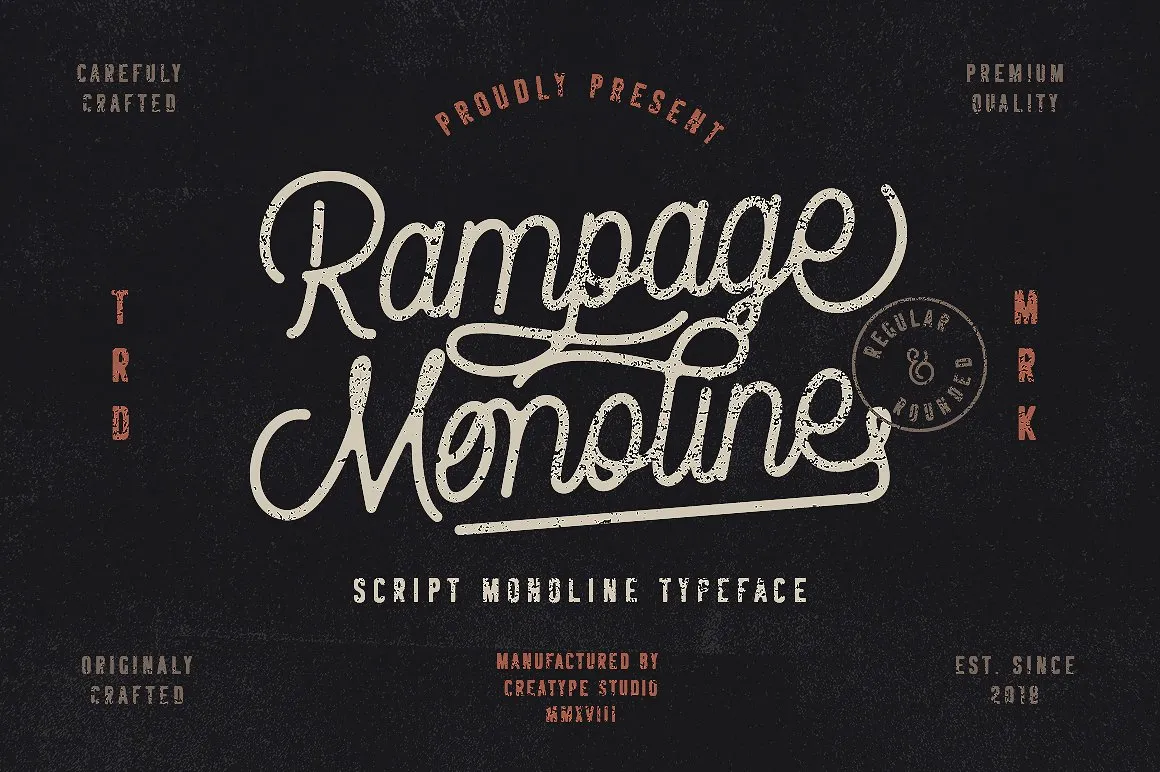
Rampage Monoline Script Font – Download Grátis
Descubra uma nova fonte tipo Rampage Monoline Script Font para seu projeto mais criativo. Esta fonte vintage monoline é uma criação do designer 24Design e traz um estilo elegante e sofisticado que adiciona um toque de movimento e elegância a qualquer projeto visual. Através de sua interface de escrita fluida, o Rampage Monoline surge tanto no formato regular quanto em versão redonda, tornando-se uma escolha perfeita para aplicativos em ambientes expositivos como branding, logotipos, design de casamentos, posts nas redes sociais, anúncios, embalagens de produtos e materiais de convite. Seja você criando arte digital ou trabalhando com fotografias, essa fonte garante um toque personalizado e autêntico sem precisar escrever a mão. Com sua versatilidade e estilo único, o Rampage Monoline é perfeito para qualquer projeto que necessite de uma pitada de escrita humana.